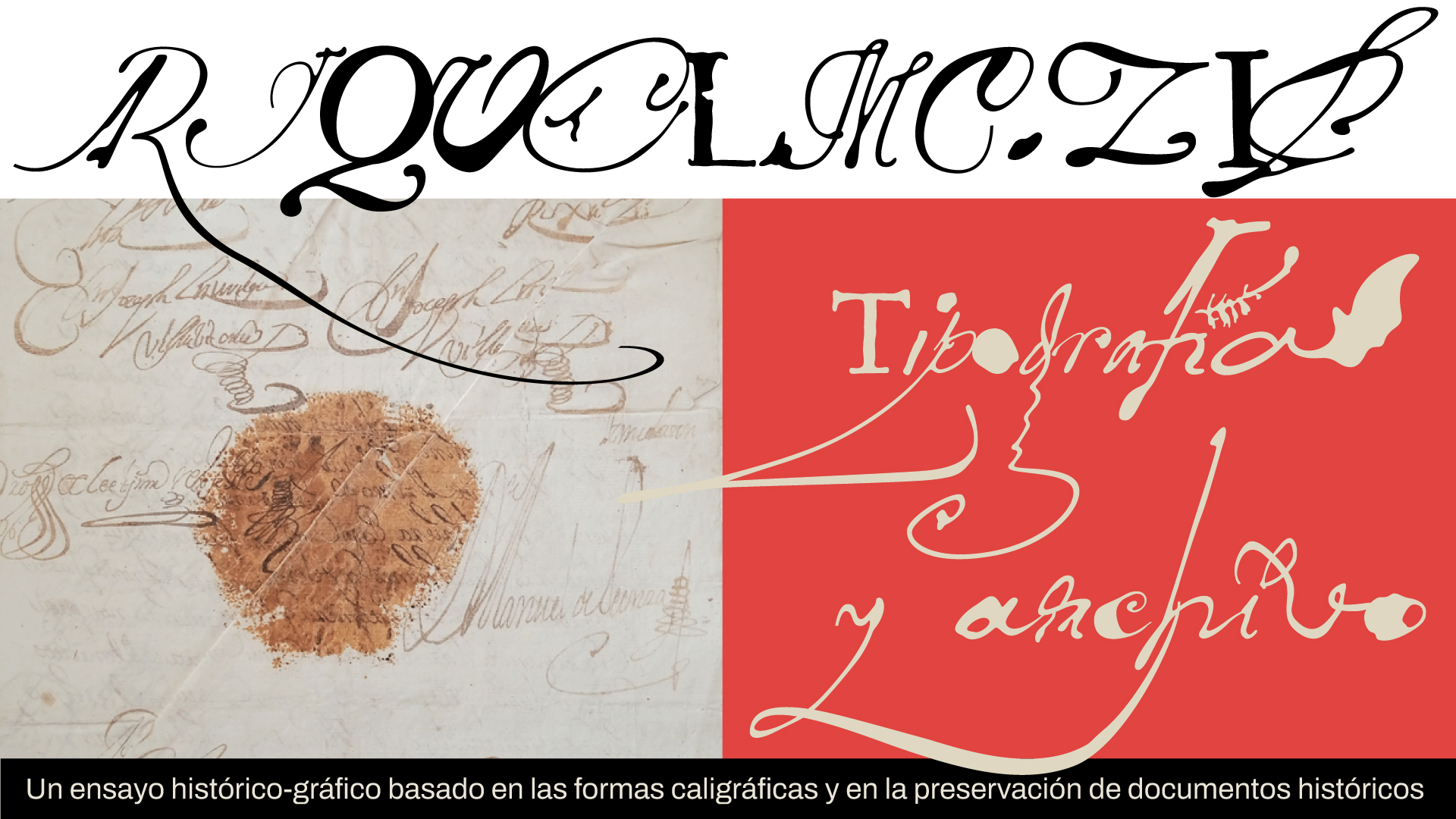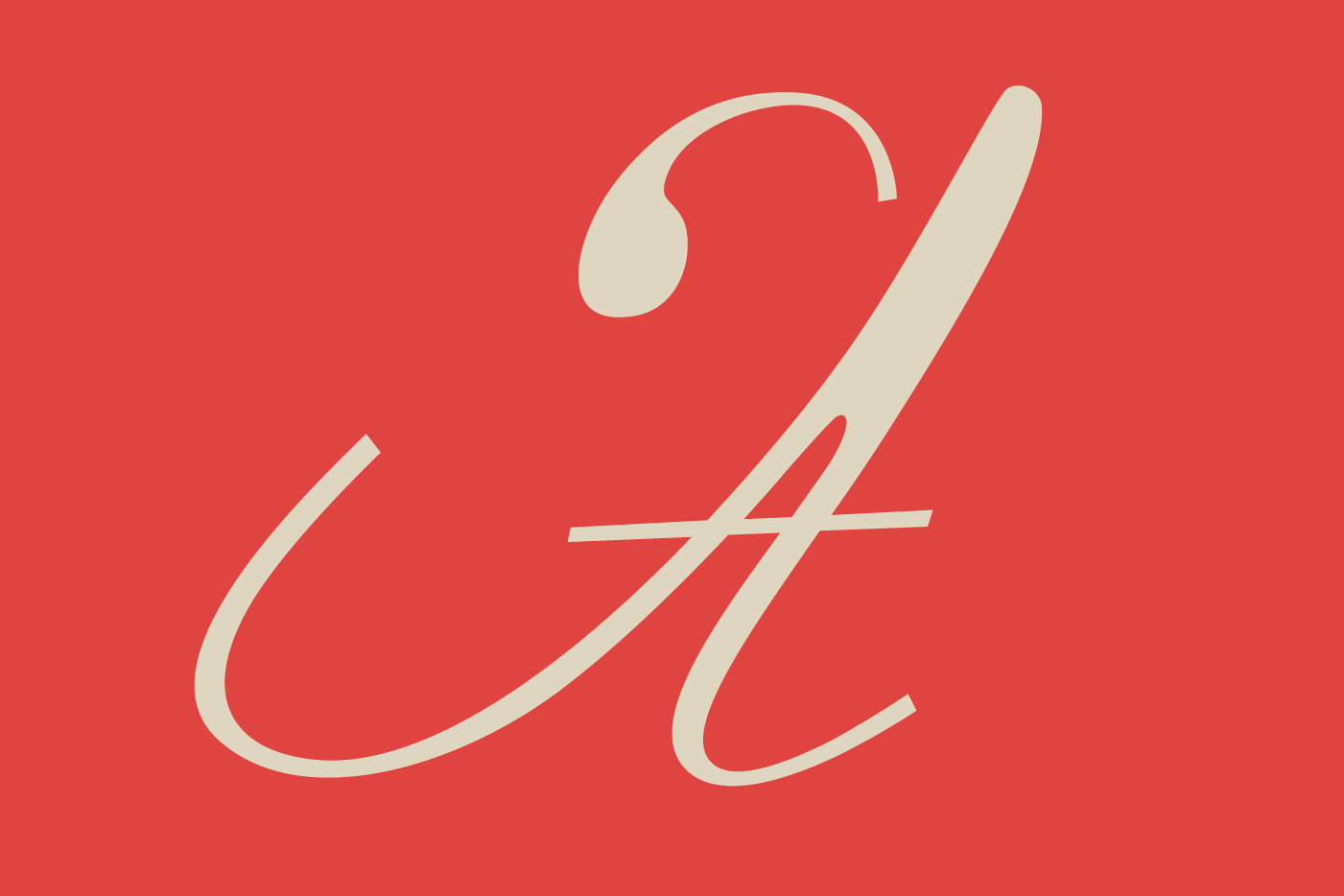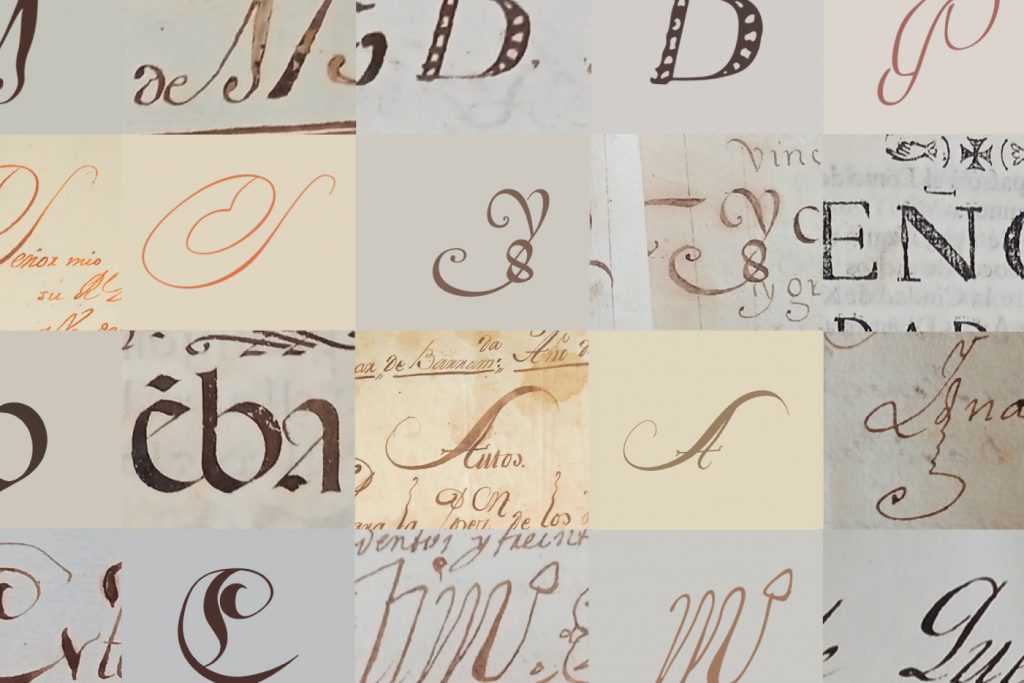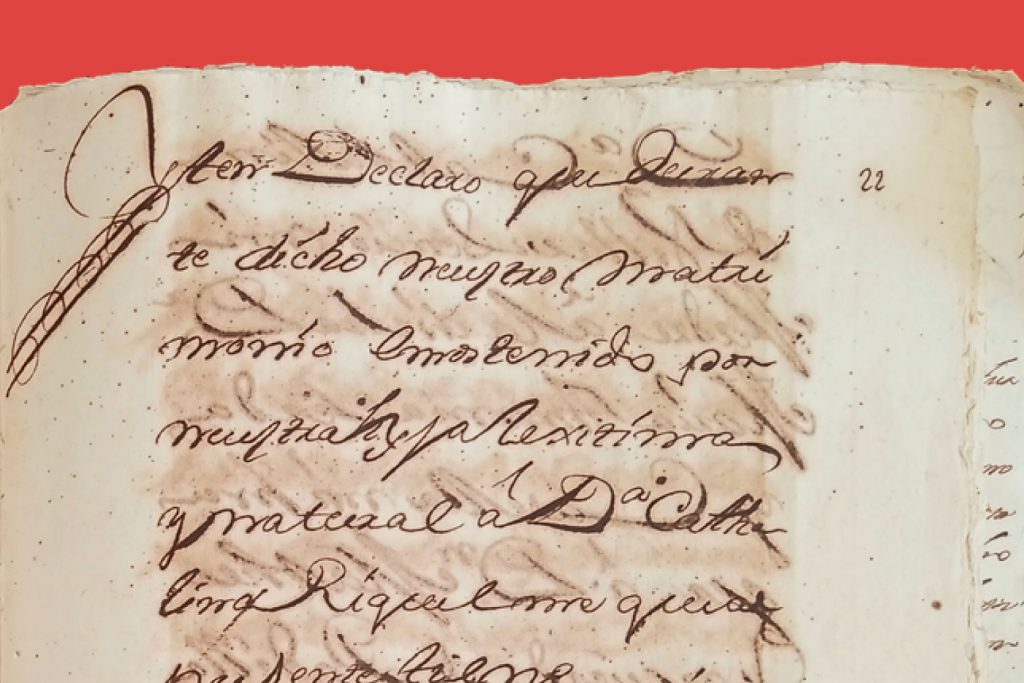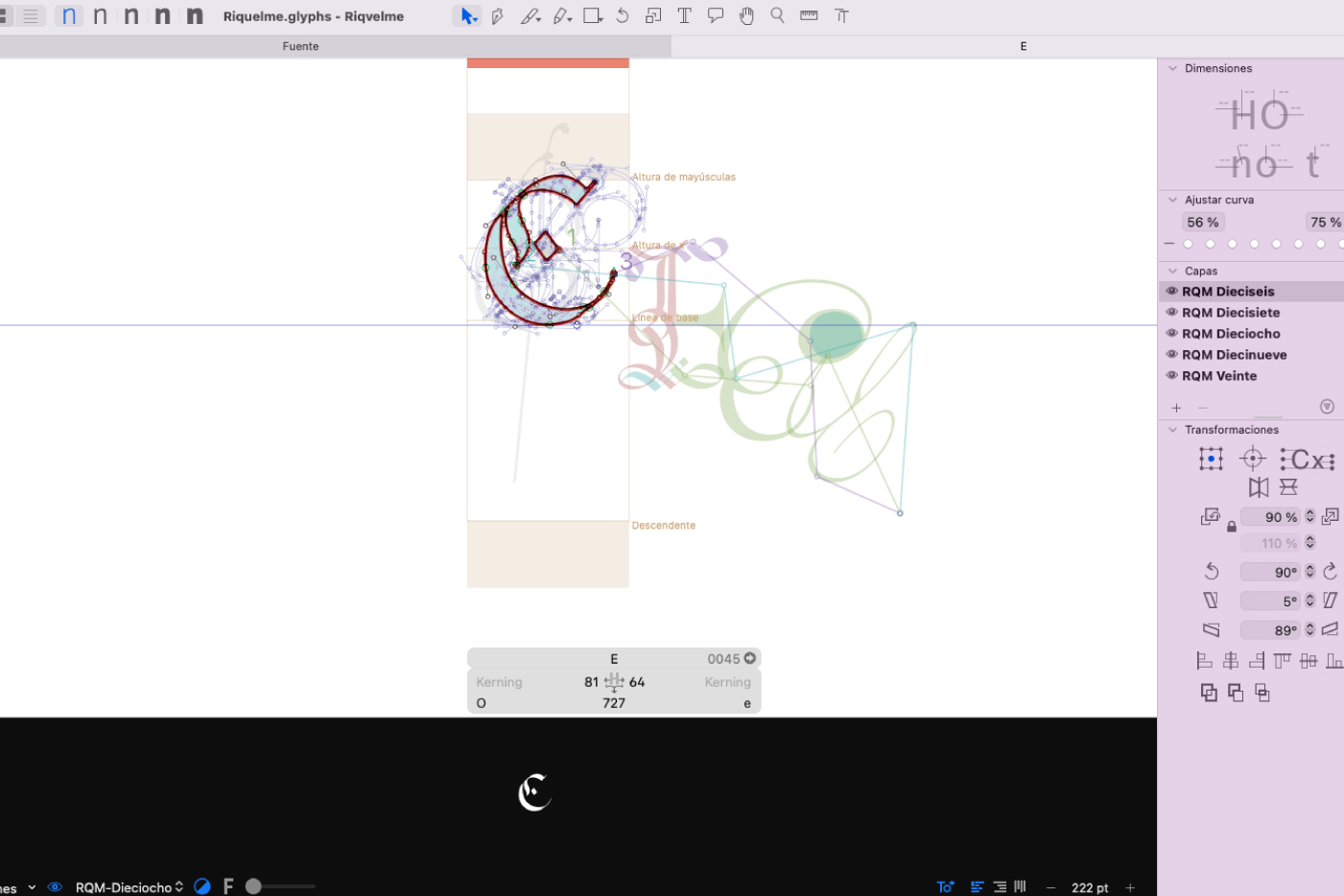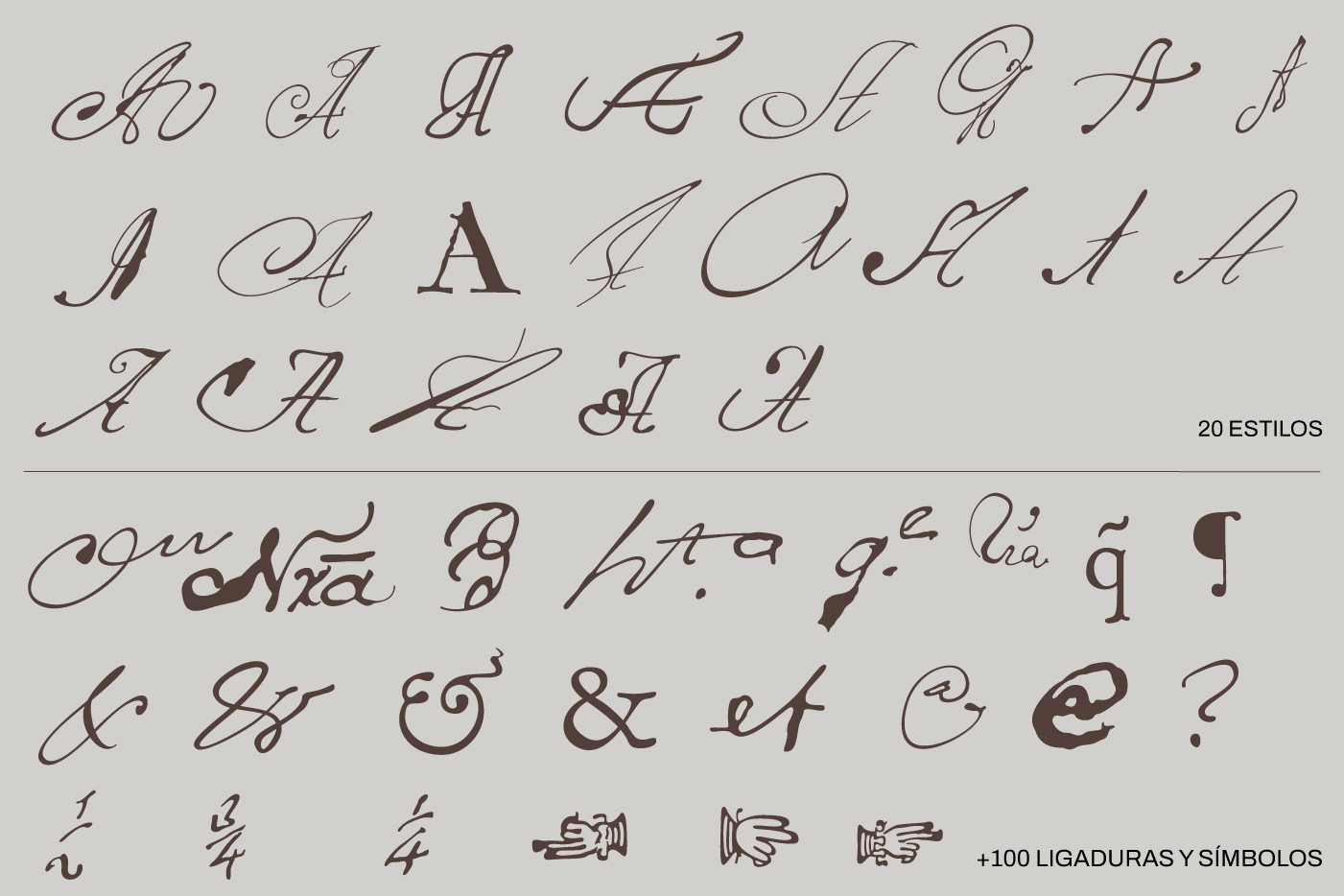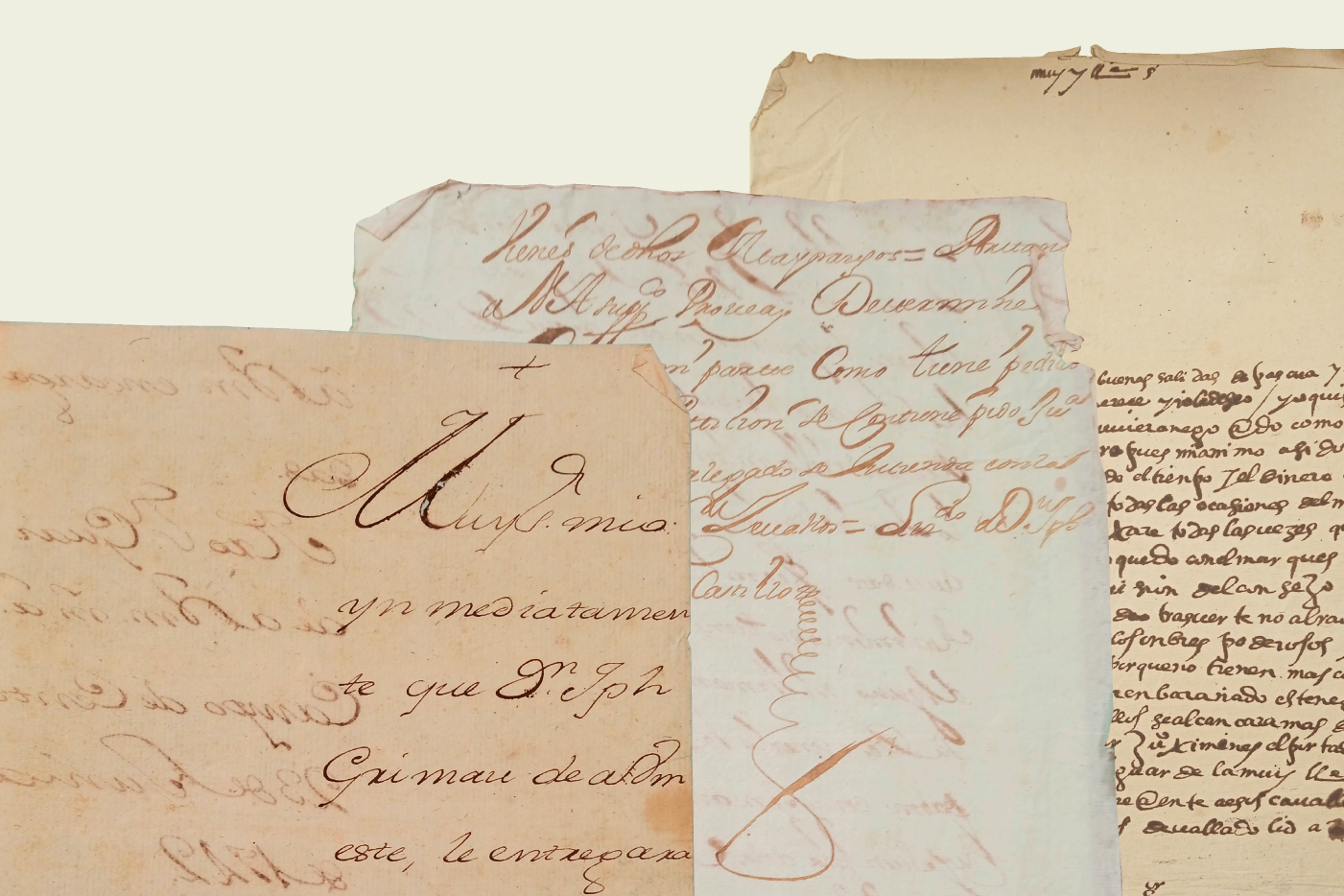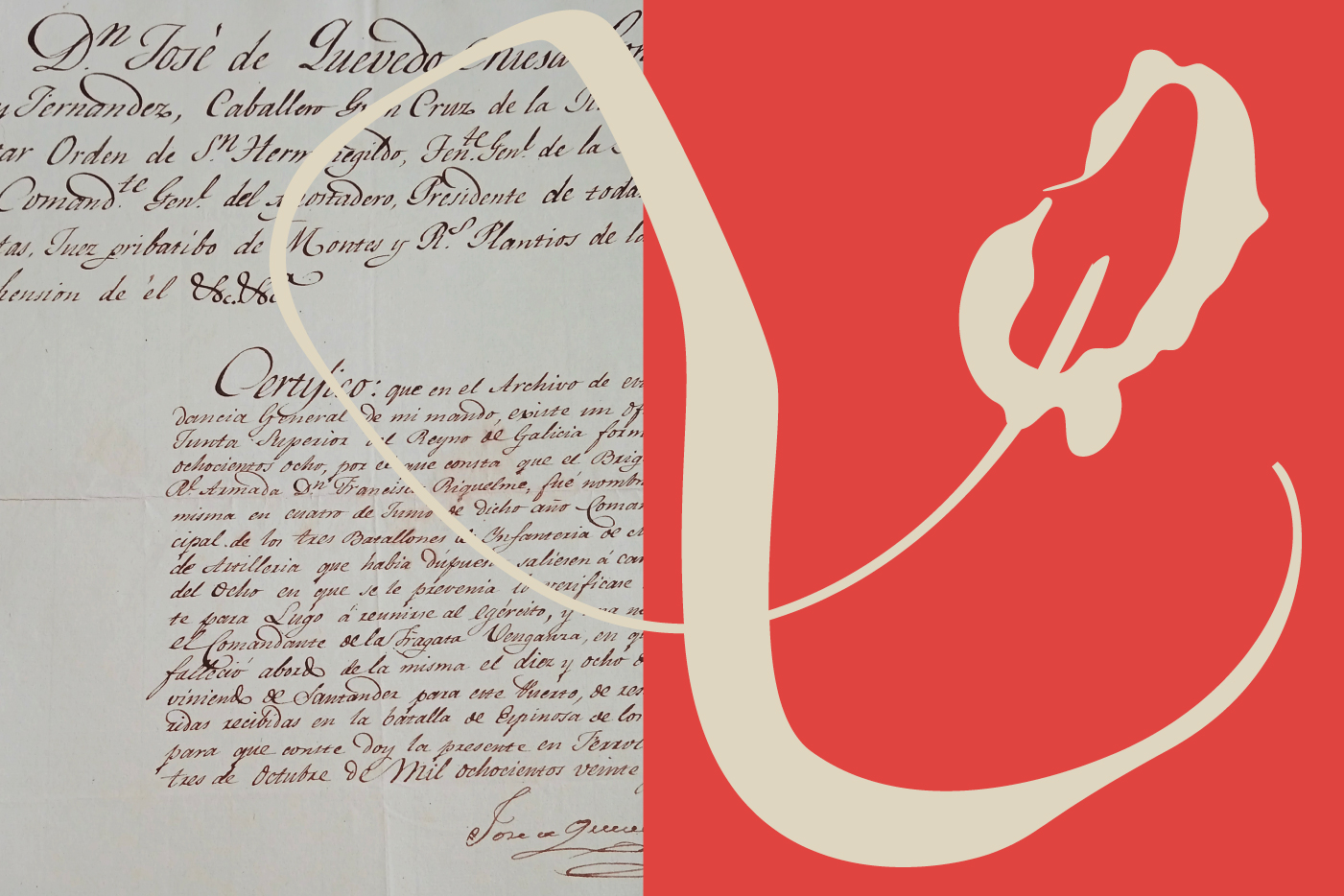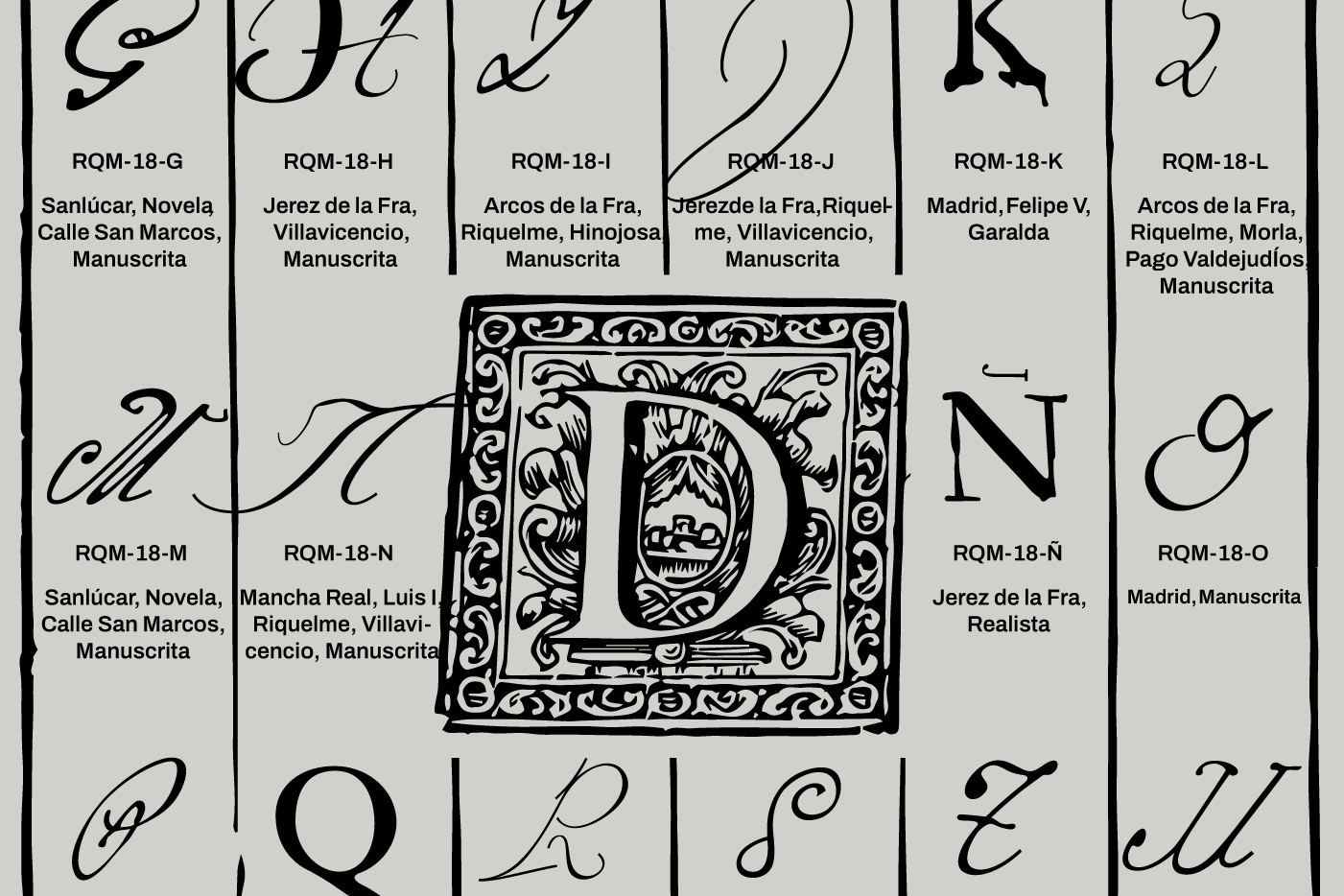
RIQUELME.ZIP
Tipografía y Archivo
RIQUELME.ZIP
Tipografía y Archivo
PATRIMONIO GRÁFICO E HISTÓRICO DE JEREZ
Un sistema con sus propias normas
Riquelme es una tipografía manuscrita contemporánea, experimental y transgresora que busca el análisis de formas románticas de la escritura del dieciocho. Flexible, ya que cuenta con más de 1.000 glifos, 20 estilos, 210 números y 40 ligaduras. Es el caos dentro del orden, es archivo y evolución formal. Es el origen y el resultado.
Desde este Despacho de Tipos, no solo fundimos letras, sino que también nos interesa romper cánones en la tipografía y concienciar, descontextualizando formas para volver a ser contextualizadas en otros medios. Por eso, ha sido diseñada a medida, siguiendo los procesos característicos del oficio. Ha sido diseñada por archiveros amantes de las Artes Gráficas.
Archivo digital y analógico
Riquelme nace a partir de la catalogación del archivo Francisco Riquelme Gil. 453 documentos que van desde el s. XVI hasta el s. XX. Para ello, categorizamos cada glifo que se extrae con cada documento, y lo complementamos generando bases de datos. También añadimos bases de datos de colores de tinta y papel. Riquelme reflexiona, de esta manera, sobre el futuro del archivo y la repercusión del oficio del tipógrafo y archivero en la sociedad.
Un viaje de ida y vuelta en el patrimonio
Riquelme busca la creación de un nuevo sistema gráfico a partir del estudio de documentos históricos. Pretende poner en valor el archivo como herramienta de trabajo, como base identitaria y como elemento primordial para la evolución cultural de la sociedad.
| Referencia: DDT-RIQUELME | Glifos: 1109 |
| Estilo: Experimental | Estilos: 20 |
| Origen: Archivo Francisco Riquelme Gil. 453 docs | Ligaduras: 40 |
Riquelme
Riquelme. La tipografía experimental con más historia de Jerez. Un sistema de combinaciones ilimitadas, con más de 1.109 glifos, 20 estilos, 210 números, 40 ligaduras y 30 alternativas en formatos .otf para impresión y .woff para entornos digitales. ¡Use Riquelme en sus proyectos de identidad o en sus proyectos más experimentales!